2023 年 33 种最佳夏季字体(免费和高级)
已发表: 2023-08-03您是一名平面设计师,正在寻找完美的字体来提升您的夏季项目吗? 别再犹豫了! 我们的博客文章“33 种最佳夏季字体”旨在帮助您找到理想的字体,以增强您的设计并捕捉阳光明媚季节的精髓。
在本文中,我们精选了 33 种夏季最佳字体,它们一定会激发并提升您的项目。 无论您是制作海滩主题海报、充满活力的夏季传单,还是热带风格的网站,我们的系列都能满足您的需求。
但为什么要为这些夏季字体烦恼呢? 那么,您是否知道使用正确的字体可以显着影响设计的情绪和感觉? 它可以唤起欢乐、嬉戏和放松的感觉——这些都是夏季的基本元素。
所以,如果你想让你的设计完美地体现夏天的精髓,融入这些字体是必须的。 让我们深入研究并发现您最喜欢的新夏季字体!
希望今年夏天为您的图形设计项目添加一些新鲜而充满活力的字体? 别再犹豫了! 在我们的“最佳高级夏季字体”部分中,我们精心挑选了 33 种顶级字体,它们非常适合为您的设计增添额外的阳光气息。
每个夏天
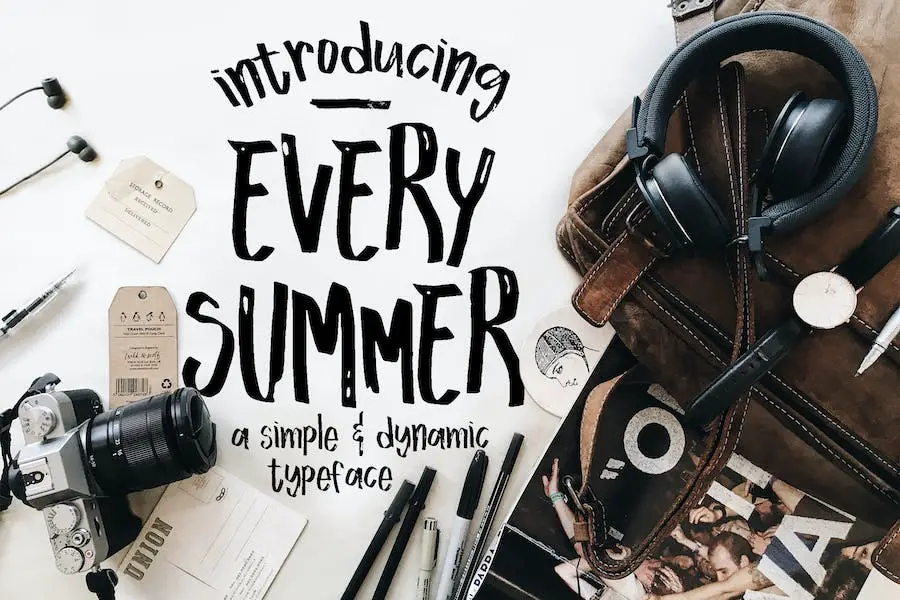
Every Summer 是一款出色的字体,可为任何设计项目增添活力和自发的触感。 这种字体使用画笔和记号笔创建,为您的作品带来独特的手工品质。
无论您是制作贺卡、设计徽标还是制作封面,Every Summer 都能提供多种功能,让您的设计脱颖而出。
《Every Summer》的突出特点之一是其完整的国际语言重音字形。 这意味着无论您使用哪种语言,您都可以为您的设计添加个性化风格。
此外,该字体还提供特殊的连字功能,使您可以在设计中创建不同的外观和风格。
每个夏天,都有无限的可能性。 其充满活力和活力的风格将为您的设计项目带来一股新鲜空气,使它们成为夏季的完美选择。 那么为什么不尝试“Every Summer”,看看它如何将您的设计提升到新的高度呢?
夏日之火
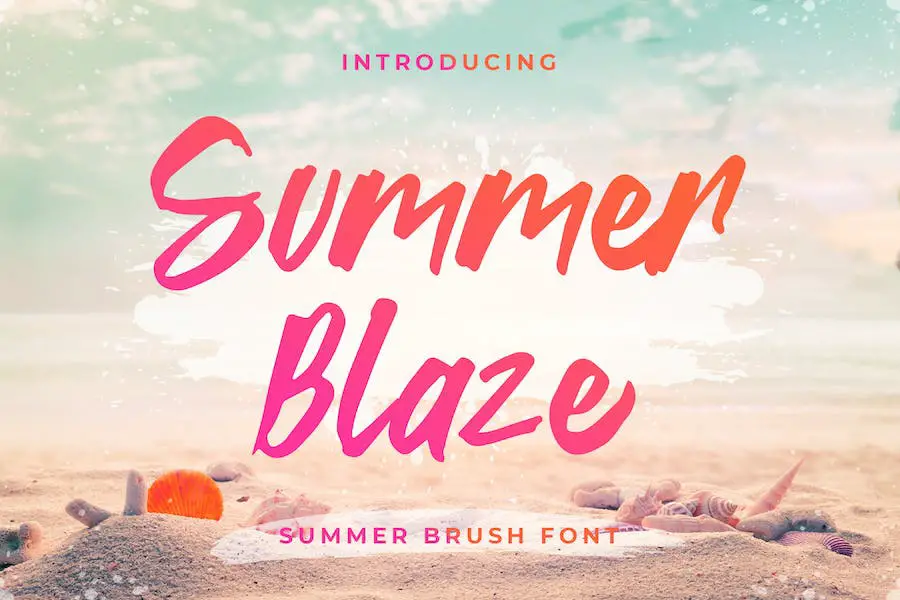
Summer Blaze 是一款梦幻般的字体,散发着海滩般的梦幻感,非常适合捕捉夏天的精髓。 这种脚本字体具有积极和轻松的氛围,使其成为增强任何设计项目的绝佳选择。
无论您是要创建徽标、邀请函还是社交媒体图形,Summer Blaze 都会增添额外的温暖和悠闲魅力。 其热带美学将立即将您的观众带到阳光明媚的海岸,并留下难忘的印象。
拥抱夏日精神,为您的设计注入夏日火焰的光芒。
永远的夏天
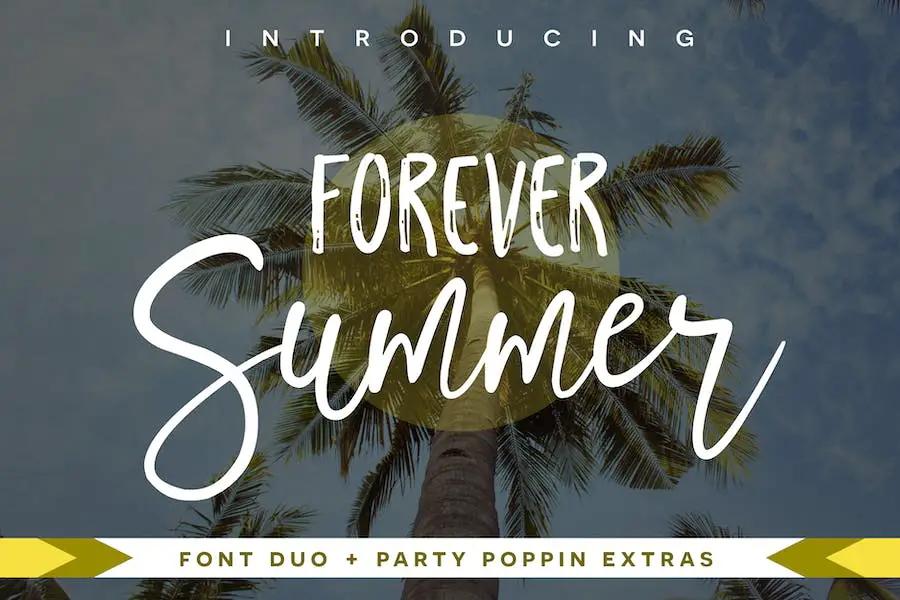
Forever Summer 是一款令人愉悦的字体组合,将诱人的脚本与迷人的无衬线字体结合在一起。 凭借其标记笔触,该字体散发出迷人且充满活力的美感,非常适合各种设计项目。
无论您是在创作印刷品、贺卡、排版引言还是品牌材料,Forever Summer 都会增添一丝俏皮感和引人注目的吸引力。
不要忘记探索这种字体附带的额外装饰品,因为它们可以轻松增强您的设计并吸引客户的注意力。
那为什么还要等呢? 潜入 Forever Summer 的世界,为您的项目注入有趣的氛围,让它们真正令人难忘。
热带
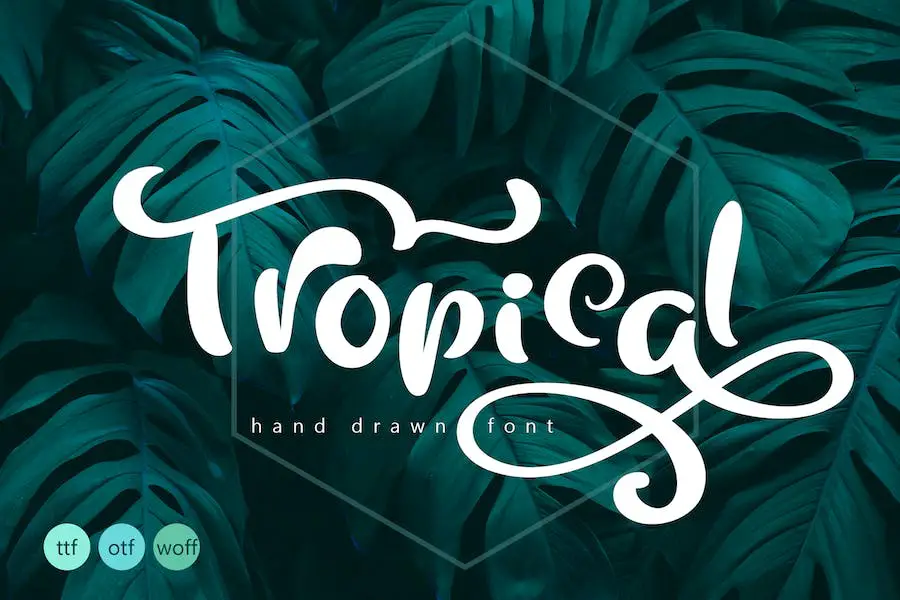
Tropical Fonts 是一种独特的手工书法字体,可为您的设计增添一抹夏日气息。 凭借其现代的显示风格和大写和小写字符的交替丰富,该字体非常适合为您的项目添加创意和艺术天赋。
Tropical Fonts 的与众不同之处在于它的可用性 - 它映射到常规键盘按键,因此您不需要任何其他程序即可使用它。 只需安装字体,开始打字,就可以尽情发挥您的创造力。
如果您希望为您的设计添加更多独特性,该字体还具有可通过 Photoshop 或 Illustrator CC 访问的替代符号。
无论您是在制作海报、徽标还是任何其他设计项目,热带字体都是一种多功能选择,可以为您的工作带来热带氛围。
那么,当您可以使用热带字体增添一丝夏日气息时,为什么还要坚持使用常用字体呢? 发挥创意,让您的设计通过这款令人惊叹的字体蓬勃发展。
漫长的夏天
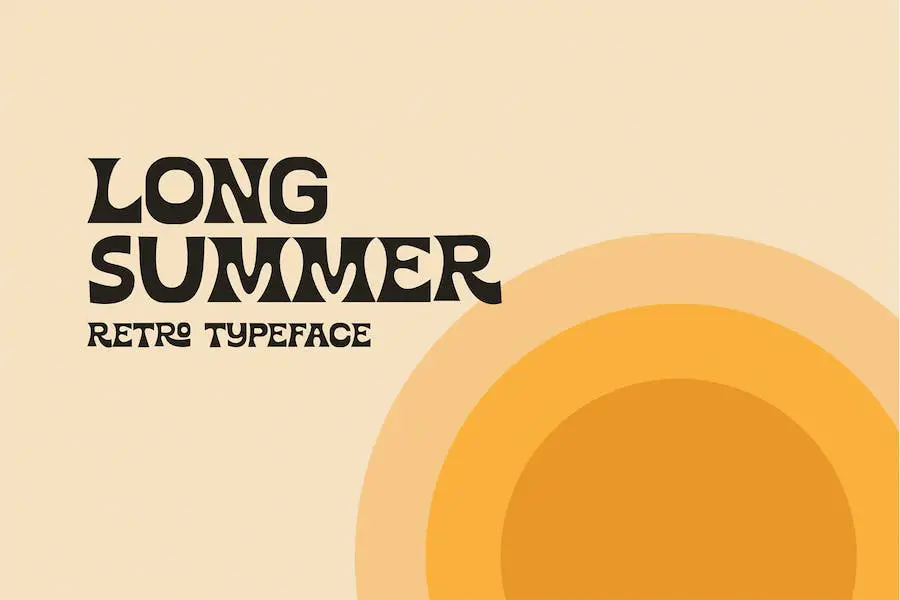
Long Summer 是一款绝妙的字体,灵感来自 60 年代和 70 年代的 Flower Children 和 Surf Babes。 凭借其复古的氛围和悠闲的风格,这种字体非常适合为您的图形设计项目增添一丝夏日怀旧之情。
该字体以其异想天开和自由奔放的设计捕捉了 60 年代和 70 年代的精髓。 其流畅的线条和俏皮的形状让人联想到阳光明媚的海滩、色彩缤纷的扎染衬衫和无忧无虑的冒险。
无论您是设计海报、徽标还是邀请函,Long Summer 都会为您的项目带来怀旧感和夏日乐趣。
该字体同时包含大写和小写字母,以及数字和特殊字符,为您提供了大量的选择。
其多功能性使其适合广泛的设计应用,从品牌和包装到社交媒体图形和网站设计。
夏季南
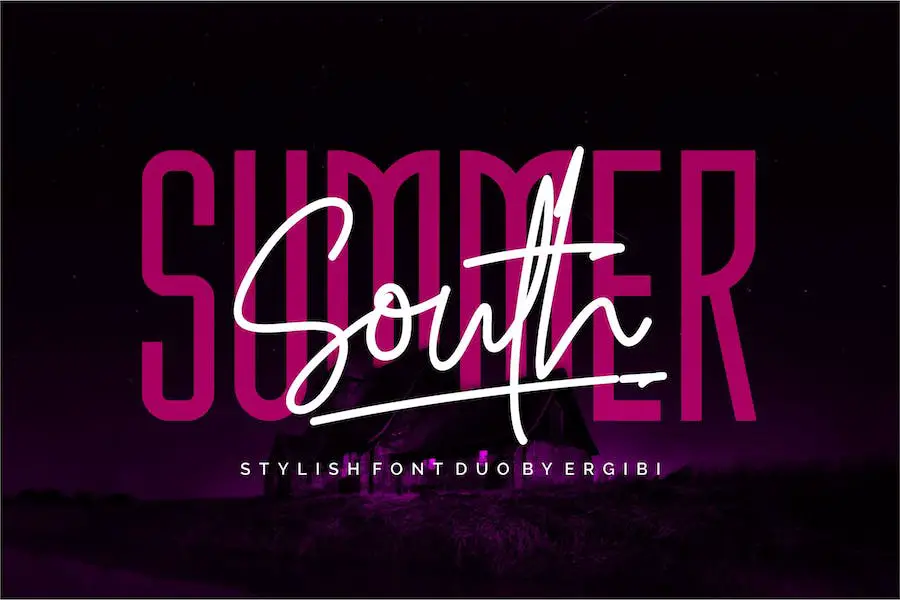
隆重推出 Summer South,这是一款美观且多功能的字体,它将手写体的优雅与现代无衬线风格融为一体。
这种字体非常适合各种创意项目,从为摄影添加水印到设计令人惊叹的徽标和品牌。
Summer South以其独特而优雅的风格为您的作品带来手写的味道,并赋予其独特而专业的外观。
无论您是在创建邀请函、广告、产品设计,甚至是婚礼设计,这种字体都一定会提升您的项目并使其脱颖而出。
但这不仅仅是美学的问题。 Summer South 还提供功能性和多功能性。 将其用于标签、产品包装、特殊活动或任何其他需要手写魅力的东西。
两种字体、脚本和无衬线字体的混合,让您可以自由地尝试不同的风格,创造出真正独特和个性化的设计。
夏日快闪
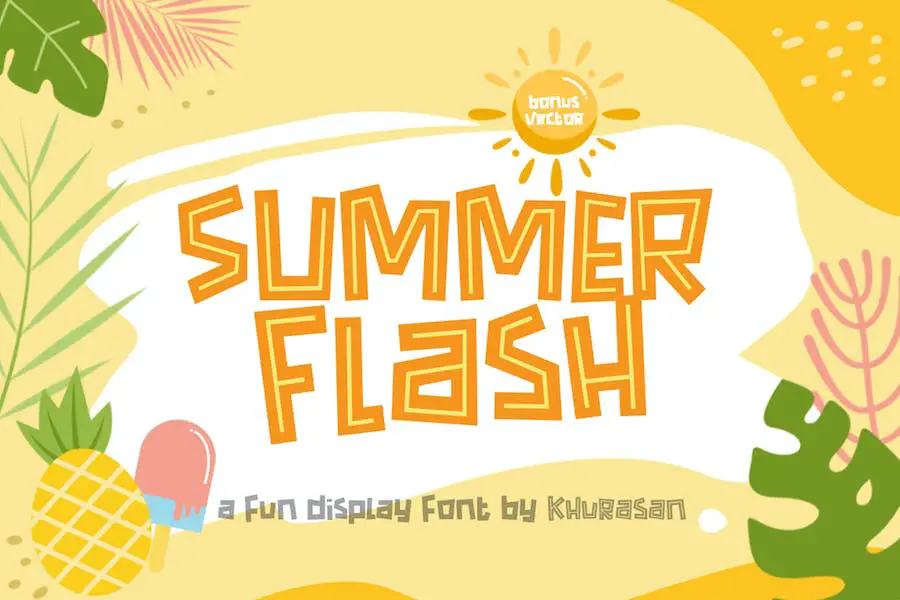
Summer Flash 是一种充满活力且时尚的字体,可为任何设计项目增添俏皮感。 凭借其大胆而现代的风格,它非常适合徽标、品牌、贺卡、海报等。
该字体具有两种不同的样式,让您可以尝试并创建独特的设计。 无论您想要大胆、引人注目的外观还是更微妙、更时尚的风格,Summer Flash 都能满足您的需求。
其清新而现代的美学使其成为夏季主题项目、节日和活动的绝佳选择。 大胆的字体抓住了有趣和活泼氛围的精髓,为您的设计增添了一丝兴奋感。
“The It”字体用途广泛,可用于各种设计应用程序。 它有助于创建独特的品牌形象并在竞争对手中脱颖而出。 它的大胆确保您的信息清晰且有影响力。
夏日闪耀
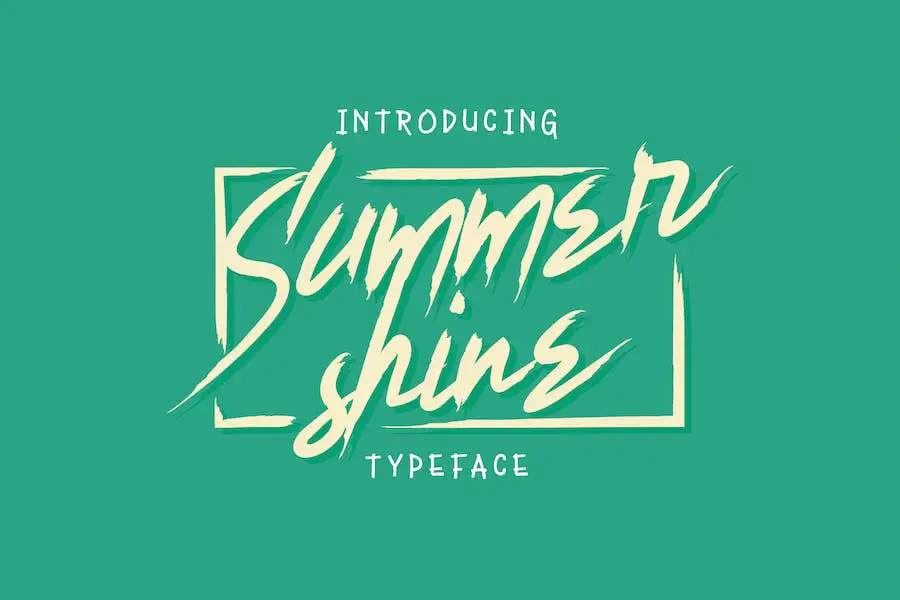
Summer Shine 是一款出色的手刷字体,非常适合您所有的夏季设计项目。 凭借其独特的笔触和俏皮的感觉,它为任何设计增添了一丝乐趣和活力。
无论您是在创建海报、社交媒体图形还是邀请函,Summer Shine 都会为您的作品带来新鲜而充满活力的外观。 其多功能性使其可用于标题和正文,确保您设计的各个方面都闪闪发光。
准备好使用 Summer Shine 为您的项目增添一些夏日光彩。 这款手刷字体非常适合您所有的夏季设计需求,将为您的创作带来清新而充满活力的外观。
其独特的笔触和俏皮的感觉使其成为任何平面设计师的必备品。 将其用于标题或正文,并观看您的设计变得栩栩如生。 发挥创意,让 Summer Shine 为您的夏季项目代言。
夏季星期三
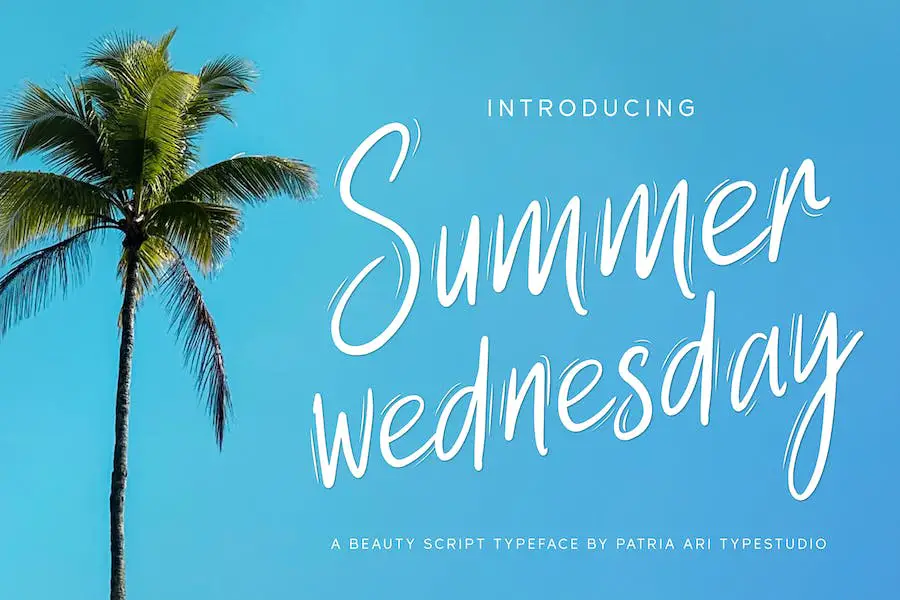
Summer Wednesday 是一款迷人且多功能的手写显示字体,捕捉了海滩氛围的精髓。
凭借其自然、手工的感觉,它是社交媒体帖子、广告、产品包装、标签和任何需要夏日气息的项目的完美字体选择。
这种海滩风格的字体为您的设计增添了独特和个性化的感觉,给它们带来温暖和诱人的感觉。 其手写风格散发出一种真实感和创造力,可以提升任何项目的水平。
无论您是制作夏季主题广告还是为海滩风格的产品设计产品包装,夏季星期三都将轻松增强您的视觉效果。
在您的设计中使用“夏日星期三”可以让您融入夏日无忧无虑和悠闲的精神。 其流畅、有机的线条唤起一种放松的感觉和在海滩边的欢乐,使其成为吸引观众注意力的理想选择。
夏季柠檬水
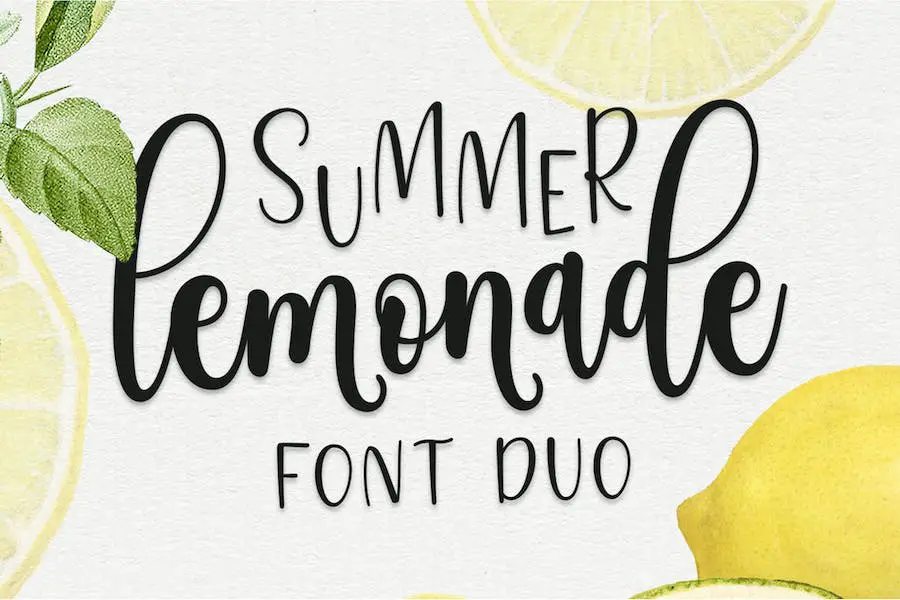
Summer Lemonade 是一款出色的新字体,可以增强您的图形设计项目。 凭借其易于使用和有趣的品质,这种字体是必须尝试的! 通过组合两种不同的字体,您有无限的可能性来创建令人惊叹的组合。
无论您需要用于徽标、社交媒体、婚礼装饰、邀请函、家居装饰、网站、博客、Instagram、名片还是品牌的字体,Summer Lemonade 都能满足您的需求。 它用途广泛,非常适合您想要的任何项目!
想为您的设计增添热带风情吗? 别再犹豫了! 夏日柠檬水将假期氛围带到您的指尖。 其清新而充满活力的风格瞬间将您带入热带天堂。
无论您是为海滩主题派对、旅游博客还是夏季品牌进行设计,这种字体都会让您的设计流行。
夏天
Summer 字体是一种时尚的手写字体,可为您的项目增添独特的触感。 其下方结构坚固,可为任何设计带来现代且有吸引力的外观。
无论您是创建邀请函、海报还是社交媒体图形,Summer 字体都会让您的文本脱颖而出。 其流畅的线条和艺术气息使其非常适合为您的设计增添优雅和创造力。
因此,如果您是一名图形设计师,正在寻找一种字体来增强项目的设计,那么 Summer 字体绝对值得考虑。
圣诞节 夏天
Christmas Summer 是一种多功能字体,非常适合寻求增强项目设计的图形设计师。 这种字体特别适合创建徽标、徽章、传单、海报等。 凭借其热带美学,圣诞夏日为任何设计增添了乐趣和活力。
这种字体的属性使其成为设计师的宝贵资产。 其独特的风格和俏皮的氛围立即引起人们的注意,并使项目脱颖而出。
大胆与优雅元素的结合创造了和谐的平衡,可用于强调重要信息或为设计增添一丝精致感。
圣诞节之夏,充满无限可能。 其广泛的角色和风格选择使设计师能够尝试并创造自己独特的设计。
无论您是在从事海滩主题项目还是只是想为您的设计添加夏日感觉,这款字体都能满足您的需求。
小夏天
隆重推出 Little Summer,这是一种简单、有趣、可爱的全大写或大写字体,非常适合各种项目。
无论您是在编写儿童读物、创建精美的引言、设计徽标,还是设计标题和标题的样式,这种字体都会为您的设计增添一丝趣味。
凭借其多功能性,Little Summer 是希望增强其项目夏季氛围的平面设计师的必备字体。 其大写风格为任何设计增添了大胆和引人注目的元素,使其适合各种创意目的。
那么为什么不使用 Little Summer 字体为您的下一个项目带来一些温暖和奇思妙想呢?
桑塔里诺
Santarino 是一种现代而清新的画笔字体,非常适合夏季。 凭借其微风和夏日的感觉,这种字体为您的所有设计项目增添了现代气息。
无论您是在制作海报、网站还是社交媒体图形,Santarino 无疑都会提升您的设计水平。
Santarino 字体的属性使其脱颖而出。 它的笔触具有自然和有机的外观,给您的文本带来手工制作的感觉。 该字体的连字和时尚的花体为您的设计增添了艺术气息,使它们具有视觉吸引力和独特性。
Santarino 最好的事情之一就是它的多功能性。 它适用于各种设计项目,从品牌和徽标到包装和邀请函。 该字体的字母清晰易读,无论是小号还是大号都易于阅读。
结论
总而言之,我们刚刚探索了 33 种最佳夏季字体,它们可以将您的设计项目提升到一个新的水平。 我们涵盖了各种风格和美学,确保这里有适合每个人的字体。
无论您是在制作夏季主题网站、节日宣传册,还是派对邀请函,这些字体都一定会增添一丝季节性的气息。